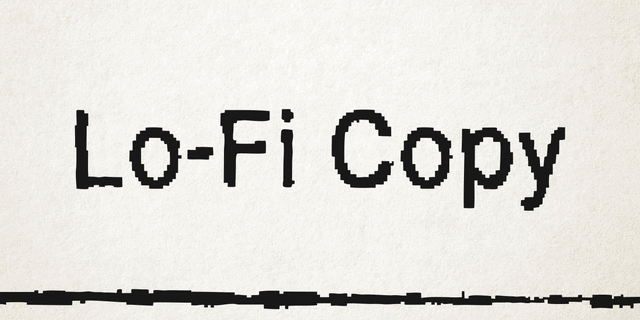
Шрифт разработан в фирме Double Alex Font Studio в 1997 году (дизайнеры Алексей Гунин, Алексей Чекулаев) по рисункам шрифта Monako фирмы Apple Computer Inc.
Ассоциации c семейством PriamojPropКачества и характер:
спокойный, ровный, убедительный, универсальный, понятный, простой, нейтральный, средний, обычный, космополитичный, ненавязчивый, стандартный, умеренный, прямой, логичный, прагматичный, практичный, твердый, невыразительный, лаконичный, офисный, строгий, серьезный, безразличный, равнодушный